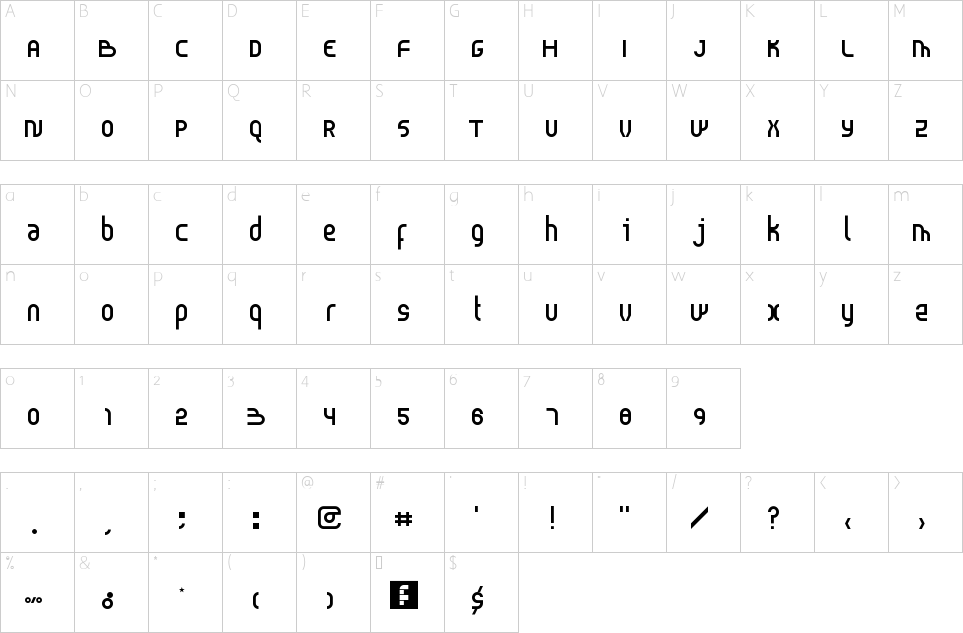
A fonte Probolinggo é uma escolha excepcional para designers e criativos do Brasil, com suas linhas fluidas e harmoniosas que remetem à cultura e diversidade do nosso país. Desenvolvida pelo designer Adien Gunarta, essa fonte oferece um toque único que se adapta perfeitamente a criações variadas, desde logotipos até letras de música. Com sua design clássico e moderno, Probolinggo é uma escolha inteligente para quem busca uma fonte grata e versátil. Desfrute de uma experiência de trabalho agradável e de qualidade, com Probolinggo, uma fonte que combina perfeitamente com a riqueza cultural brasileira.